使用書体:理杏美琉丸体ファミリー
使用箇所:パッケージの各所
理杏美琉丸体ファミリーを採用した上海ネピアの「聚能吸 キッチン」が、今までとは全く違うイメージの新パッケージに生まれ変わりました。スタイリッシュでファッショナブルな雰囲気が漂い、キッチンペーパーとしての用途だけでなく、キッチンまわりに置いておくだけで、空間を爽やかに演出します。
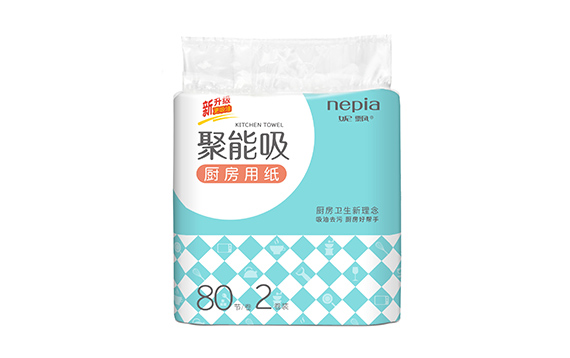
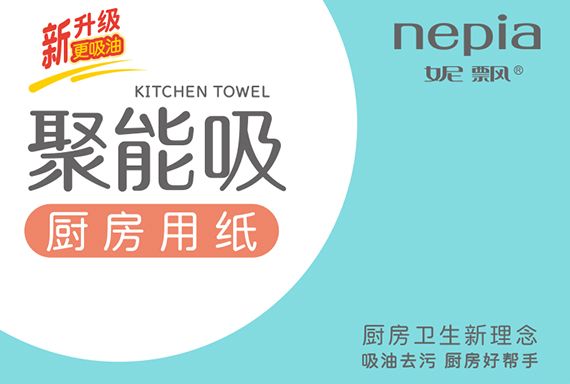
理杏美琉丸体は、店頭等で目立たせたい製品タイトルをより個性的に演出します。ワンポイントで使っても可愛らしいイメージが表現でき、ます。パッケージデザインや広告のキャッチコピー、店頭POPなどでの使用がおすすめで、消費者の目を惹くフォルムが特徴です。